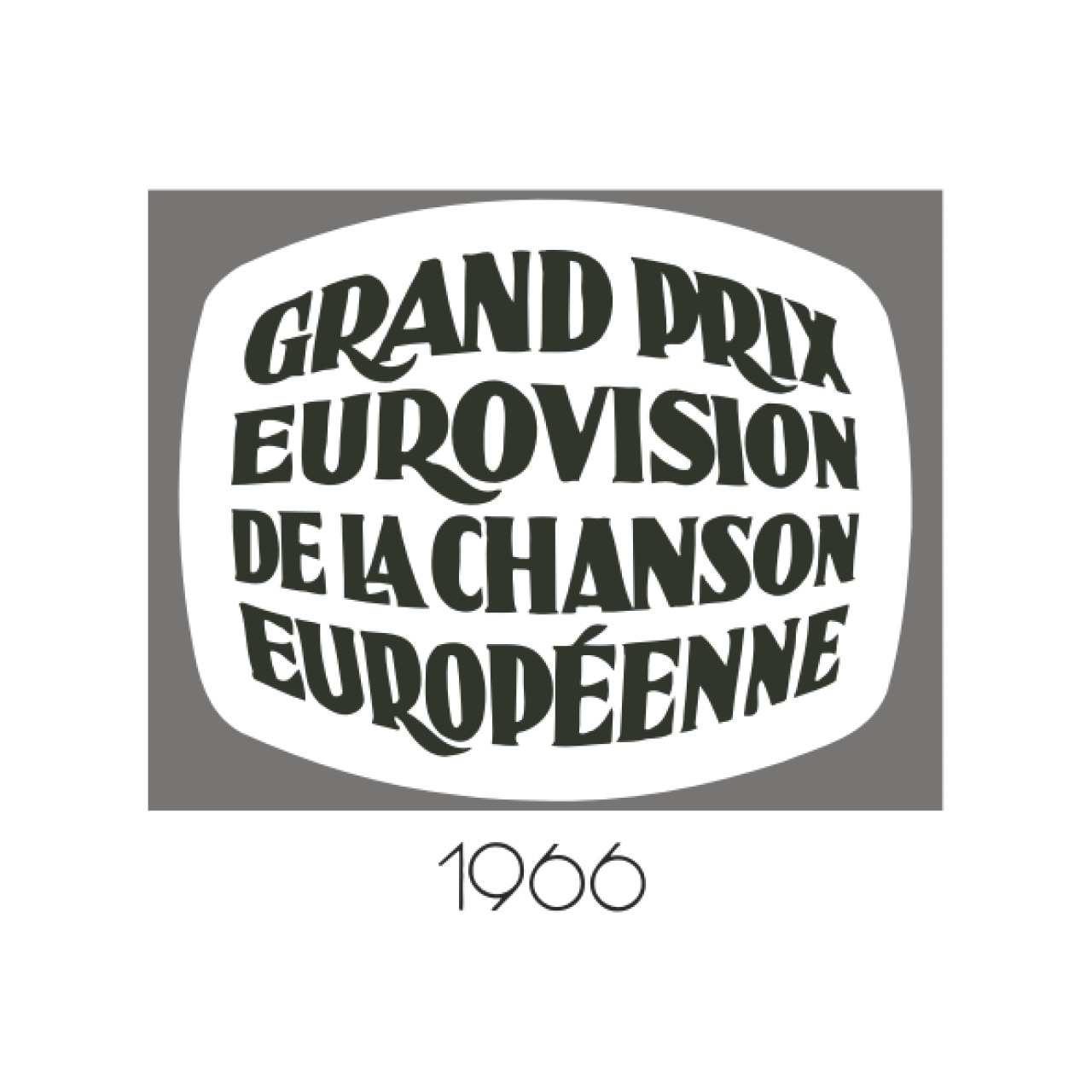
Suche Schrift vom Eurovision Song Contest 1966
Hallo, ich suche die Schrift, die 1966 beim Eurovision Song Contest Logo verwendet wurde.
Speziell die Schrift die oben für den Schriftzug verwendet wurde, nicht die für die Jahreszahl.
Am Besten genau diese Schrift, kann auch zum Kaufen sein.
Und genau die wirds auch der beste Profi kaum finden. Vielleicht höchstens eine entfernt ähnliche Ideenvorlage, denn in dieser Zeit dauert es noch 4 Jahre, bis Peter Karow das digitalisieren von Schriften erfindet, danach dauerte es noch bis 1984 bis endlich Adobe mit Postschript den einsatz digitaler Schriften möglich machte.
In der damaligen Zeit hatten die Grafiker der Film-Firmen und  Fernsehanstalten gar keine andere Möglichkeiten, als solche Logos, wie auch komplette Vor- und Nachspänne komplett von Hand zu schreiben oder zu zeichnen.
Also in diesem Fall erst mal eine Skizze, dann ein Bogen stabiles Zeichenpapier und hier die Bögen mit einer biegsamen Leiste als Hilfslinien einzeichnen, dann die Buchstaben zuewrst in Blei einskizzieren, korrigieren und letztlich in Tusche die Konturen einzeichnen, Hier mit Lineal und Kurvenlinealen, z.B. Burmeister-Kurvensatz die Buchstaben sauber zeichnen, Mit Tusche dann ausfüllen, und danach Hilfslinien (wo die im Repro stören, weil etwas zu kräftig ausradieren (vieles plättet Lith-Film prima weg) - Da hat man schon mal n Tag dran gesessen...
Ach ja, auch als man mit Letraset und Konkurrenzprodukten endlich Druckschriften sauber aufs Papier bringen konnte, gingen auch nur gerade Schriftzeilen, solche Verzerrungen benötigten noch sehr lange Langwierige Handarbeit.
Vielleicht fallen uns ja ähnliche Schriften ein, die wir dem/der Threadersteller/in an die Hand geben können?
Eigentlich bedaure ich fast, in einer Zeit gelandet zu sein, wo vielfach einfach nur eine (einigermaßen) passende Schriftart ausgesucht, oder bestenfalls oft ungelenk daran herumgezupft und geschnippelt wird, geht es darum, ein Logo zu entwerfen.  Irgendwie ist auch eine Menge an Kreativität dabei verloren gegangen. Ich erinnere mich noch gut, wie Spannend es noch in meiner Schülerzeit war, in eine andere Stadt zu reisen, und auf allen möglichen Beschriftungen spannend neue Schriftstile zu erblicken, egal ob jetzt Straßenschilder (siehe CAT Linz oder Immermann von mir) oder Ladenschilder, Autobeschriftungen oder selbst Schilder vom Kleingartenverein, oder erst recht Grabdenkmale. Ebenso natürlich auch Filmtitel oder sogar handgemalte Großfilplakate an Kinos, wo nicht selten der Filmplakatmaler sich nicht an die im Film verwendete Schrift gehalten hatte, sondern eher seiner persönlichen Handschrift folgte. Selbst in der Zeit, in der Kinos sich nur noch mit Porno-D-Movies über wasser zu halten versuchten, waren die Plakate typografisch gesehen nicht unbedingt langweilig. Schade nur, so etwas wurde kaum fotografisch festgehalten.
Das, was wir heute noch sehen, sind ja meist die Sahnestücke, die überlebt haben. Vieles war vielleicht "kreativ" aber mehr auch nicht. Wo heute Brush Script, Banco oder Comic Sans als Folie im Schaufenster klebt, wurde früher™ bestimmt auch nicht handwerklich perfekt und künstlerisch gearbeitet*. Die Spanne von eben mal was hingepappt und aufwendigen Logos und Fotografien** ist heute noch genauso groß:
Wir bewundern heute, wie sauber und gleichmäßig manche schreiben konnten – z. B. für Film(zwischen)Titel – aber das ist ja nun nicht mehr nötig, wenn es fertige Schriften dafür gibt. Eigenständigkeit ist aber mit der Vielzahl an Fonts dennoch möglich.
* Ich erinnere da mal an das So(a)fteis mit dem eigenartigen f – das war auch nicht wirklich toll gemacht ...
**  Wo du schon von Filmplakaten sprichst: Manche Fotos sind derart bearbeitet, dass man auch eher von Malereien sprechen kann und ob es wirklich so toll ist, wenn da jedes Kino sein eigenes Süppchen kocht, ist aus Gestaltersicht auch zu hinterfragen.
Da gebe ich dir natürlich recht. und dein genanntes Beispiel mit dem ulkigen f ist ja tatsächlich kein Meisterwerk gewesen, wobei das f eben aus Arno Dreschers Arabella stammt, und wo wir ja auch schon ein etwas besser gelungenes "Drescher-Zitat"  in Form einer Leuchtreklame hatten. Da wurde ja gerade auch dieses f gesucht.
Aber letztlich birgt eben auch die noch so stümperhaft aber selbst erdachte Schriftart eines Anstreichers, der sich als Schildermaler versuchte, trotzdem Ideen, die ein besserer Schriftgestalter aufgreifen könnte. Klebt da aber Brush Script, Banco oder Comic Sans als Folie im Schaufenster, steckt darin aber eben keine neue Idee mehr.